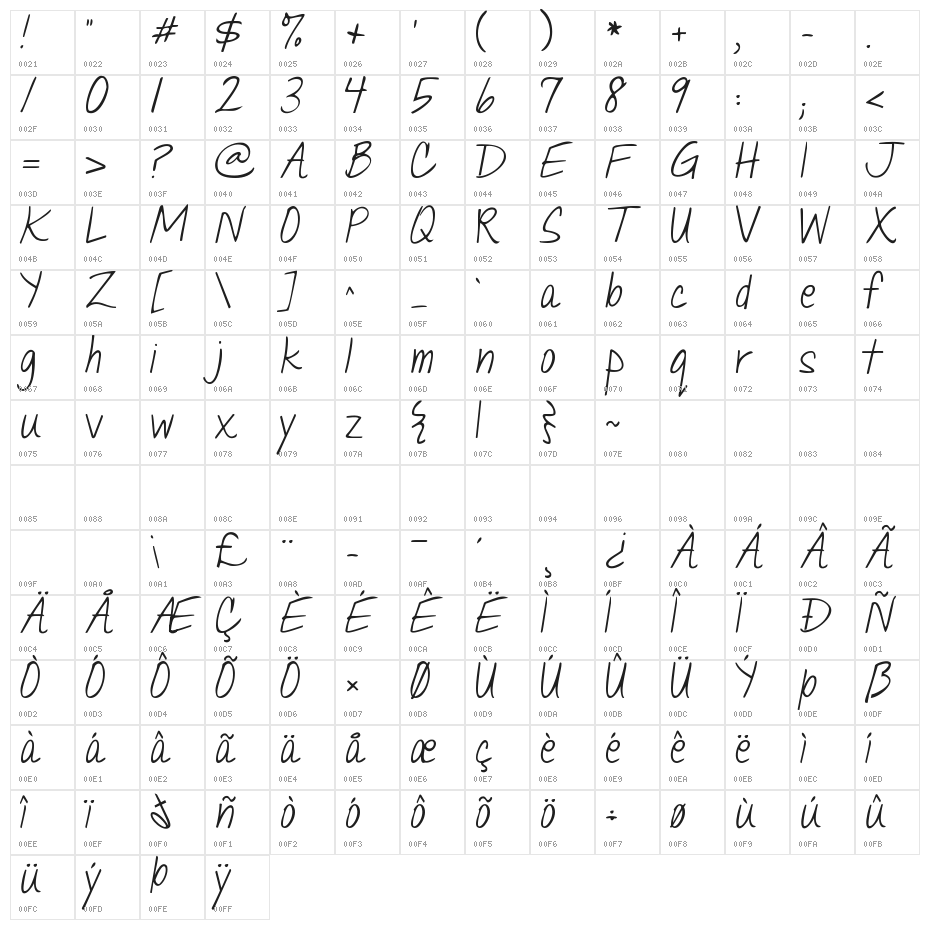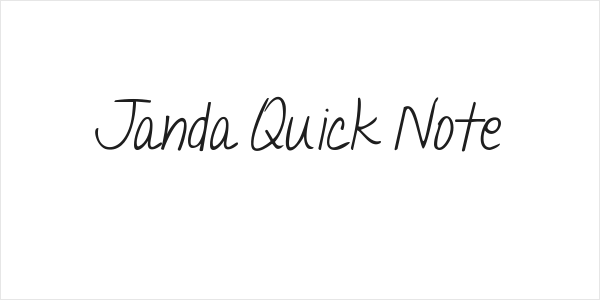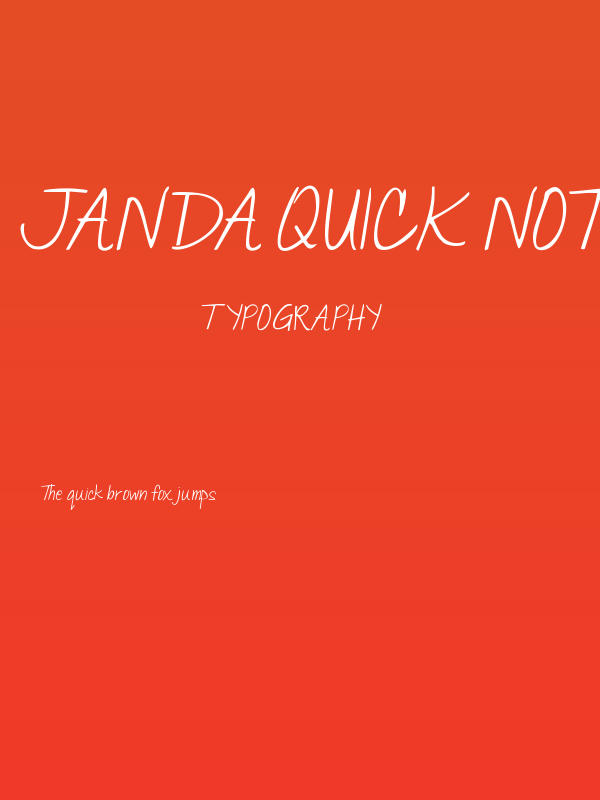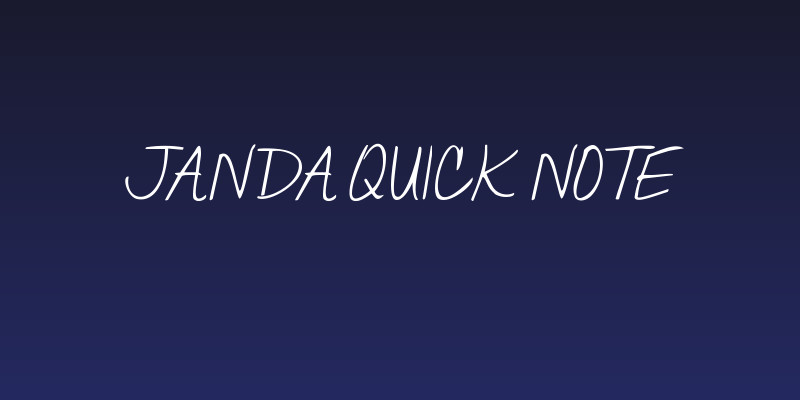
Janda Quick Note Font
| Stil general | Casual, Handwritten |
| Caz de utilizare | Headlines, Informal text, Creative projects |
| Proiecte propuse | Ideal for greeting cards, personal blogs, and creative projects needing a personal touch. |